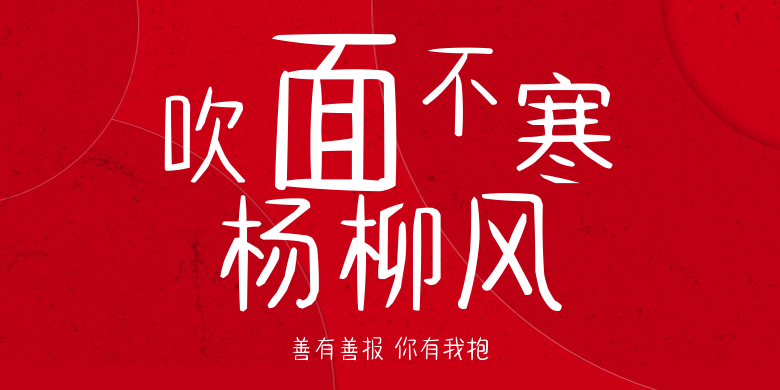
善有善报 你有我抱
善有善报 你有我抱,这款字体结构工整、笔画清晰,兼顾美观与易读性,适用于标题、正文、海报、包装、LOGO 等多种场景。字形优雅稳定,风格百搭耐看,适配日常排版与创意设计,让文字呈现更舒适、更具质感。善有善报 你有我抱一笔一画,皆是细节,以均衡的比例、流畅的线条打造舒适视觉体验,字形端正大气,风格简约现代。无论是商业设计、品牌宣传还是日常排版,都能轻松驾驭,让文字更有格调与力量。善有善报 你有我抱字体下载。